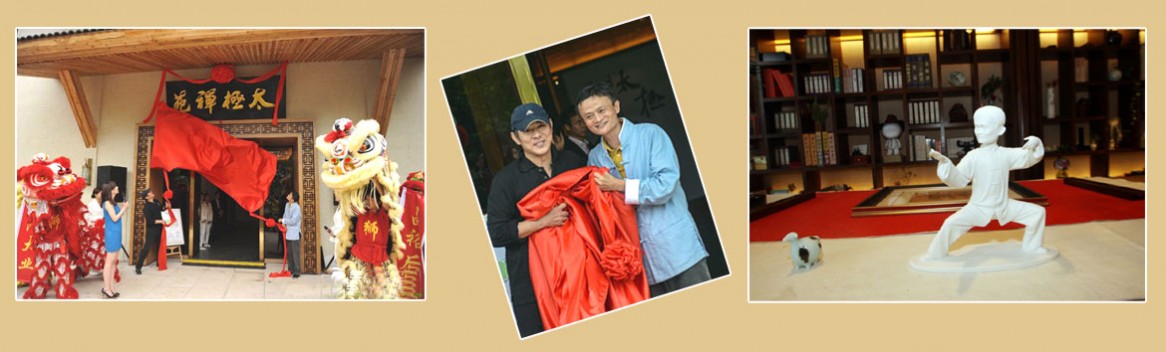
字體名稱:太極禪苑禪毅體
太極禪苑禪毅體是由阿里巴巴太極禪苑擁有版權的字體,該字體以行草風格創(chuàng)作,自然流暢,大方中透露出一種禪文化的陰陽平和,由黃毅先生書寫該字體原稿,由葉根友字體團隊制作。
太極禪苑是由馬云和李連杰共同創(chuàng)辦的推廣中國傳統(tǒng)文化的場所,也是阿里巴巴集團的一個文化中心,其理念為推廣太極文化,建立新文化圈子,在圈子內(nèi)融合道家、儒家、佛家文化精粹,以儒釋道理念之本來做企業(yè)管理,做人之本,修煉個人能力,提高企業(yè)綜合能力。在院長陳偉先生的運籌下,已經(jīng)融合了多級文化,如阿里巴巴太極圈、太極拳、阿里養(yǎng)生日以及太極禪苑牛人俱樂部、阿尼斯紀錄等,并簽約了多位在其領域內(nèi)有一定影響力的新銳人物,如淘女郎、阿里巴巴上市敲鐘人、星緣守護公益發(fā)起人何寧寧;畫家毛經(jīng)卿以及書法家葉根友等。